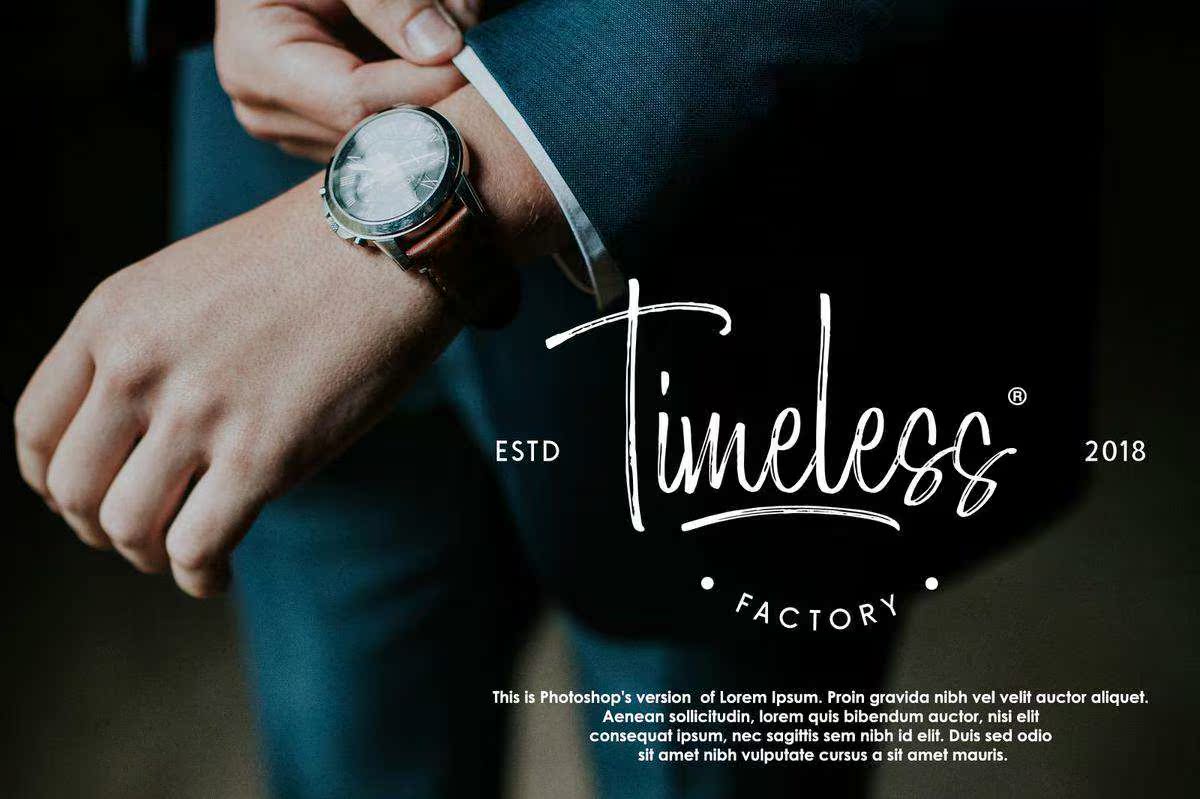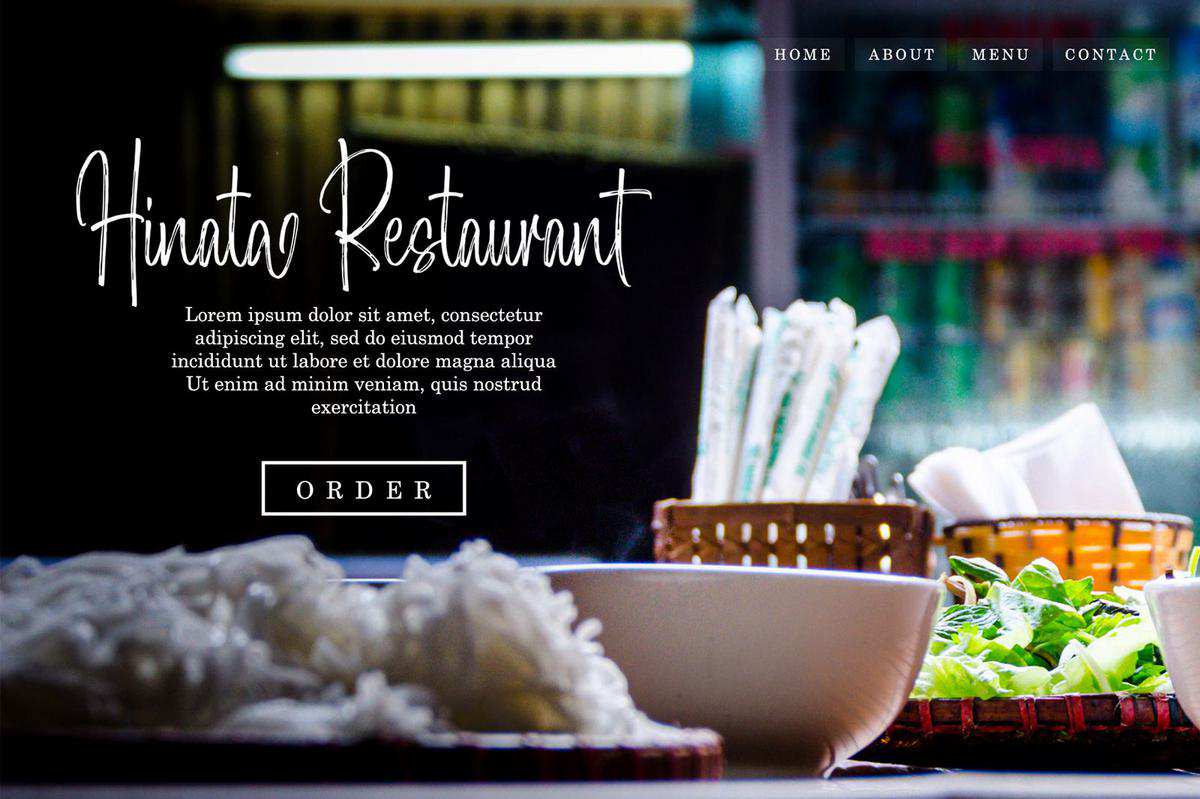
Morristone是一种典型的字体,具有自然流动的外观和内部文字。该字体可使您的设计看起来真实且手工制作。Morristone非常适合用于您的签名、标识、邀请牌、报价、网站标题设计、包装、,Branding and More。此字体可用于设计您的创作。Morristone是一款典型的字体,具有自然流畅的外观和内部纹理。此字体可使您的设计看起来真实可信,并采用手工制作。Morristone非常适合用于签名、标识、邀请牌、报价、网站标题设计、包装、,Branding and More.This Fonts始终是设计您所创建的。